思い描いたデザインを実現するうえで、適切なフォント選びは欠かせません。
実はあまり好きではなかったHelveticaですが、Helvetica Nowは発売と同時にその佇まいに魅了され、すぐに飛びつきました。
王道、スタンダードなHelveticaの安定感を継承しつつ、垢抜けていて、スッキリ目に気持ちいい。Neue Haas Groteskに近い印象も。
Helveticaが気に入らなかったMonotypeディレクター/ニックスさんの「最愛の人を新しい角度から眺めて再び恋に落ちるように、Nowが世の中から再評価されてほしい」というストーリーも好きです。
「筑紫書体シリーズ」が大好きなのですが使い勝手という面で一番重宝しそうな「筑紫ゴシック Pr5」が推しです。
Lで大きめ薄めの色と、Eで小さめで強い色など、大きさ・太さ・色で全然表情の違う面を見せてくれます。
様々な欧文フォントとの組み合わせもすごく良く本文でも読みやすい。
どこか「懐かしさ」や「あたたかみ」を感じる字形で、感情が文章に乗りやすい大好きな推しフォントです。
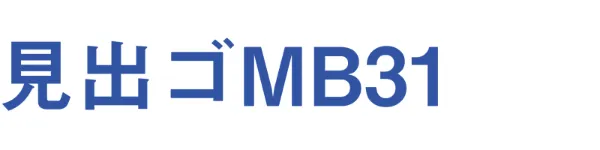
一見シャープな印象ですが、細部まで作り込みが高く、大きなサイズで使用すると粗がなくその真価を発揮します。 文字のバランスが絶妙で、インパクトがありながらも読みやすさを損なわないのが特徴です。広告のコピーやキャッチフレーズなどでよく使われているフォントで、これを使うだけで広告っぽいメジャー感の演出とメッセージに力強さと存在感を与えることができます。また、和文フォントでありながらモダンでスタイリッシュな雰囲気も演出できるので、さまざまなジャンルのデザインに活用できる汎用性の高さも魅力の一つです。
大学でグラフィックデザインを体系的に学び、初めて出会ったのが「筑紫明朝」でした。4年間の授業で、恩師が美しい書体なのだと何度も語っていたのがとても印象的で思い出深い書体です。そんな私も筑紫書体の美しさに魅せられた一人。躍動感があるのにどんな媒体でもぴたりとはまる洗練された佇まい、インク溜まりが垣間見える趣のあるひらがなの造形。どれをとっても美しいこの書体をもっとたくさんの人に知ってもらいたいです。
90年代のDTP黎明期は和文フォントが少なくて、その際に大変重宝したのがこのロダンというフォント。
築地体初号ゴシックみを感じるかなのお陰なのか、横組にした時いい感じに組め、リズムよく読めるのが地味に好きなんです。今見ると一周回って新しい気がして、また推してみたいと思うフォントです。
曲線と直線のバランスが絶妙で、文字の形が独特です。モダンでありながらも温かみを感じさせるデザイン。幅広いウェイトが揃っており、多彩なデザインに対応可能です。タイトルなどで大きく使ってみたいフォントですね。Optimaは美しさと使いやすさを兼ね備えたフォントだと思います。
デザイナーをはじめた頃、引き出しを増やそうとよくファッション雑誌のレイアウトを見比べていました。
その時に目を引いたのがBodoniで、アルファベット一文字でもアクセントになる強さが好きでした。
Webフォントとして使えるのであれば、装飾としてだけでなく、文章の流れの中からも存在感を出せそうです。
強い主張はしないのに、芯のある印象が魅力的な中ゴシックBBB。一見ベーシックだけれどデジタルっぽすぎず、よく見るとシンプルながらもややクラシカルであり、さわやかさも兼ね備えているところが、わたしの推しポイントです。
ふところが狭めのゴシック体で読みやすい正統派フォントなのですが、さりげなく癖があって好きです。セザンヌは起筆部にセリフがついていたり、素朴なかわいらしさが醸し出される緩やかな曲線だったり、どの文字も表情豊かなデザインで愛しいフォルムでたまりません。それでも、きちんと可読性があるのが良いところ。ついつい使ってしまう推しフォントです。